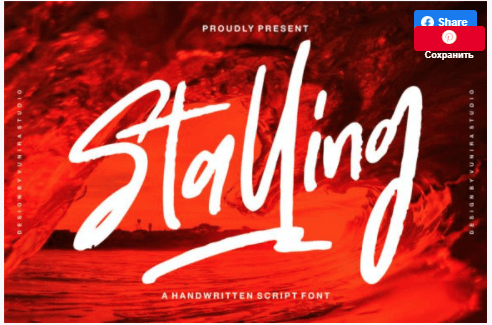
Stalling Font
Stalling - это крутой, стильный, асимметричный и немного жуткий рукописный шрифт. Добавьте его уверенно к своим любимым творениям и позвольте себе удивиться результату.